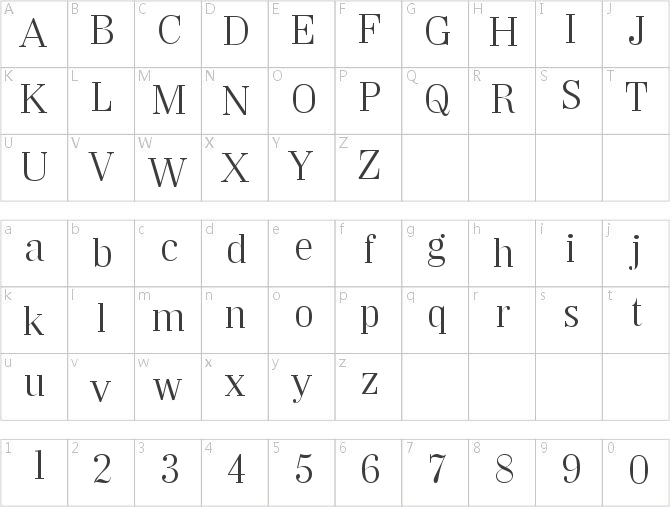
字体名称: Wicker
Wicker Light SF
Wicker Light SF介绍
Wicker Light SF字体字库是一款让人赏心悦目、百看不厌的英文字体,适合各类广告和产品包装设计应用,字体大小0.06MB,格式为ttf字体,上传用户是诚泽永信,作者/版权方为未知
Wicker Light SF效果图